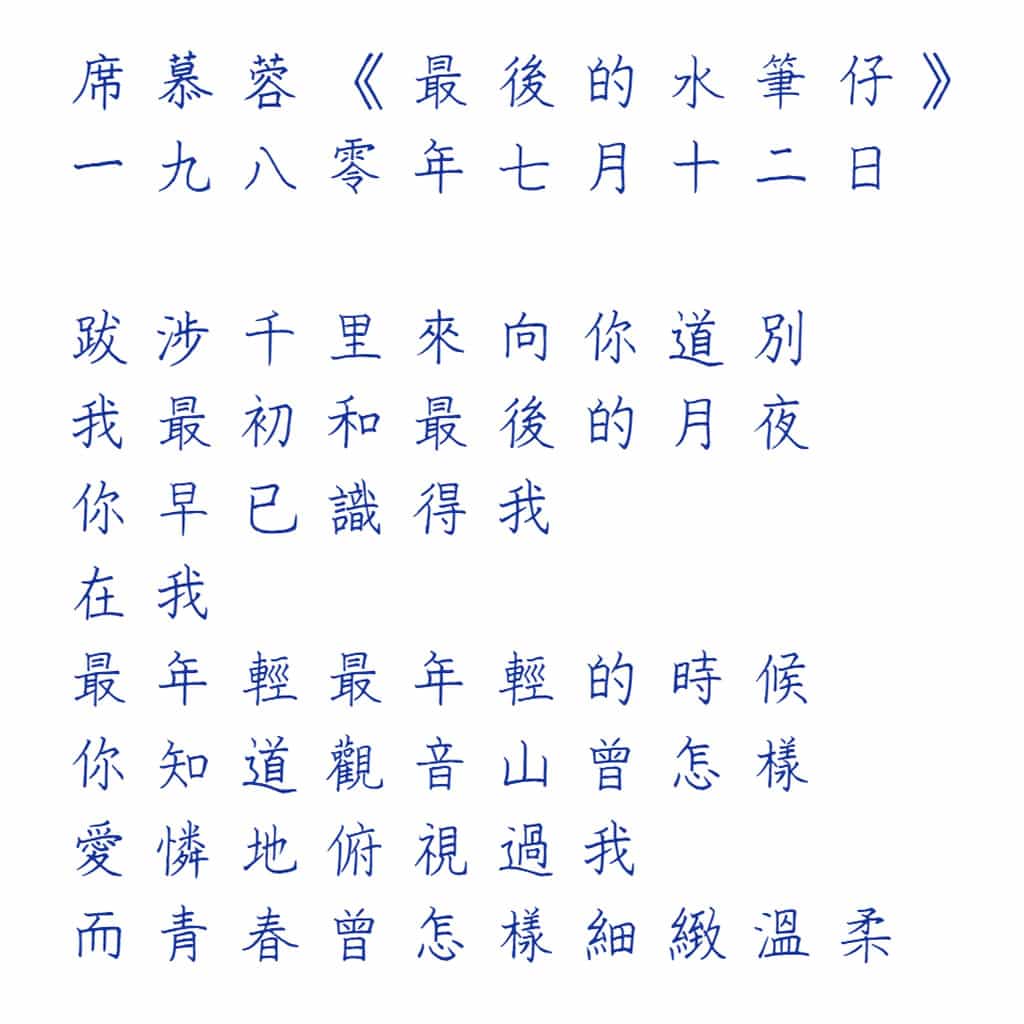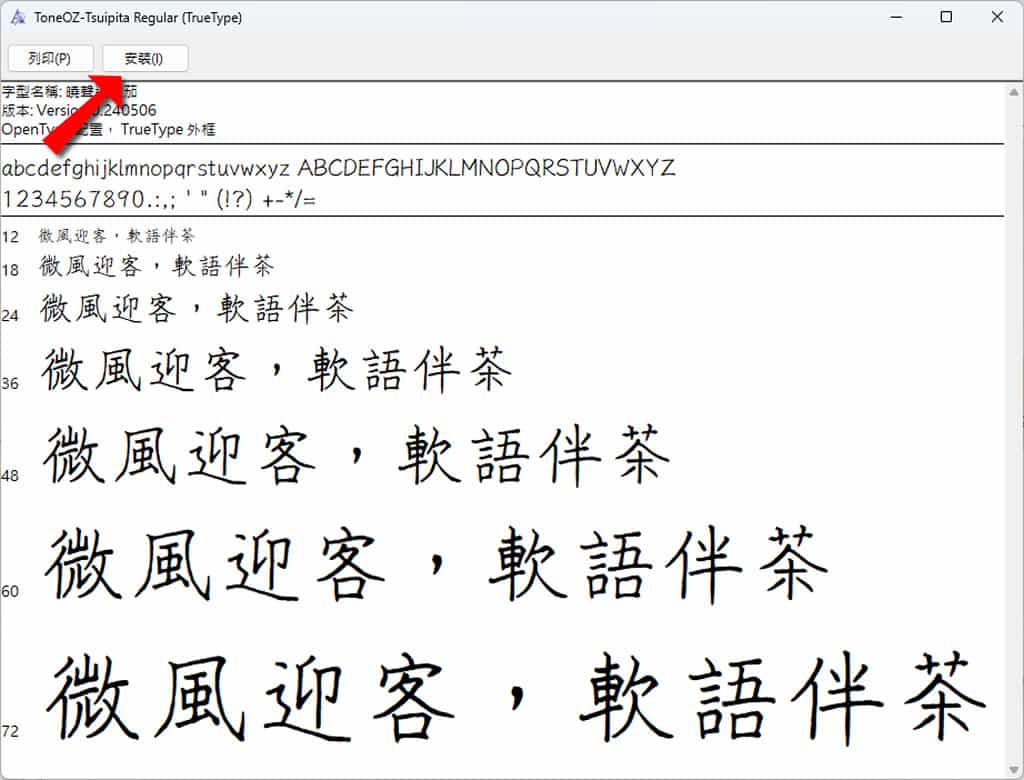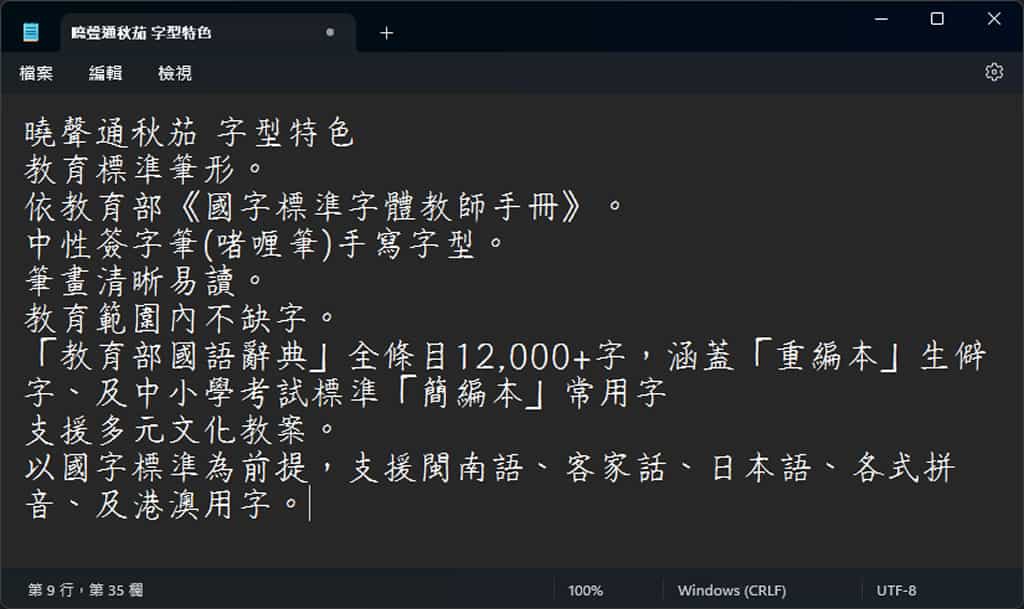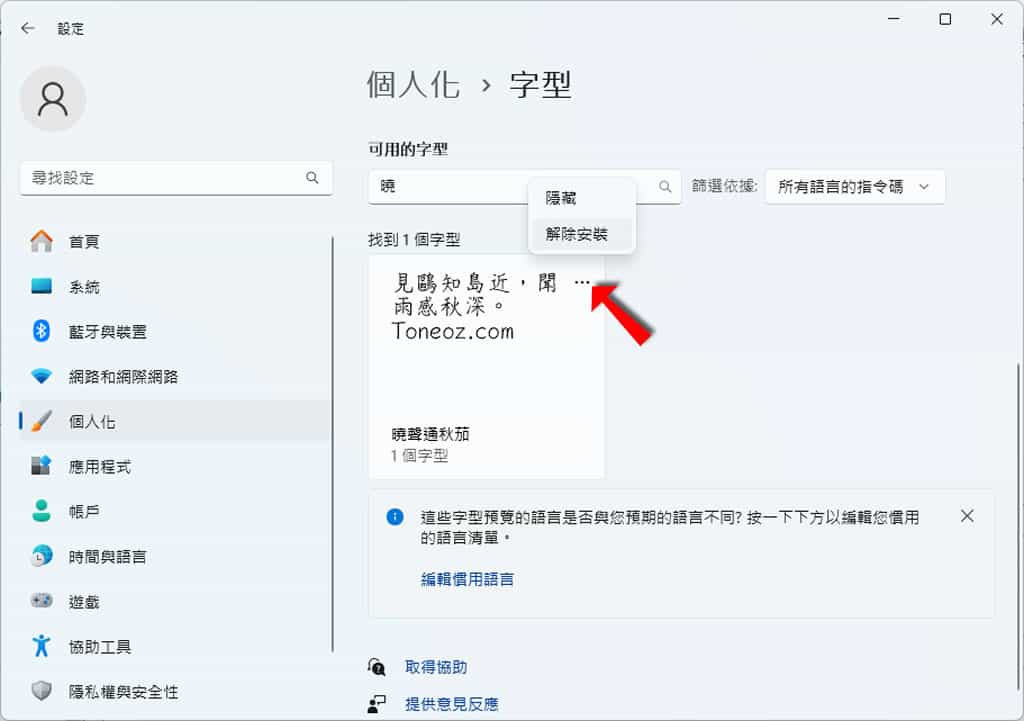
「曉聲通秋茄」是一套源於「隨峰體」的手寫中文字型,具有教育標準筆形、教育範圍內不缺字( 支援小學「國語課本」生字詞索引,涵蓋康軒、南一、翰林三家出版社的各學年 )及以國字標準為前提,支援閩南語、客家話、日本語、各式拼音、及港澳用字等特點。根據作者的自述,其用一年的時間逐字將筆畫依照《國字標準字體教師手冊》進行修改,再手工補足國語辭典中的次常用及異體字,新造字數超過原始母字型總字數一倍以上。確保在廣泛文學閱讀時不缺字,每個字的筆形都能與教學一致,老師們能安心在各種教案情境下運用。「曉聲通秋茄」提供僅漢字、注音版、拼音三種版本可供選擇。「曉聲通秋茄」為開放原始碼,不但免費且可商用。
「曉聲通秋茄」是一套以國字標準為前提且涵蓋教育部國語辭典所有條目的手寫中文字型,不但筆畫清晰易讀且教育範圍內不缺字,還支援閩南語、客家話、日本語、各式拼音、及港澳用字,且還有注音、拼音版本可供選擇下載,幫助老師們可以輕鬆創作教案。